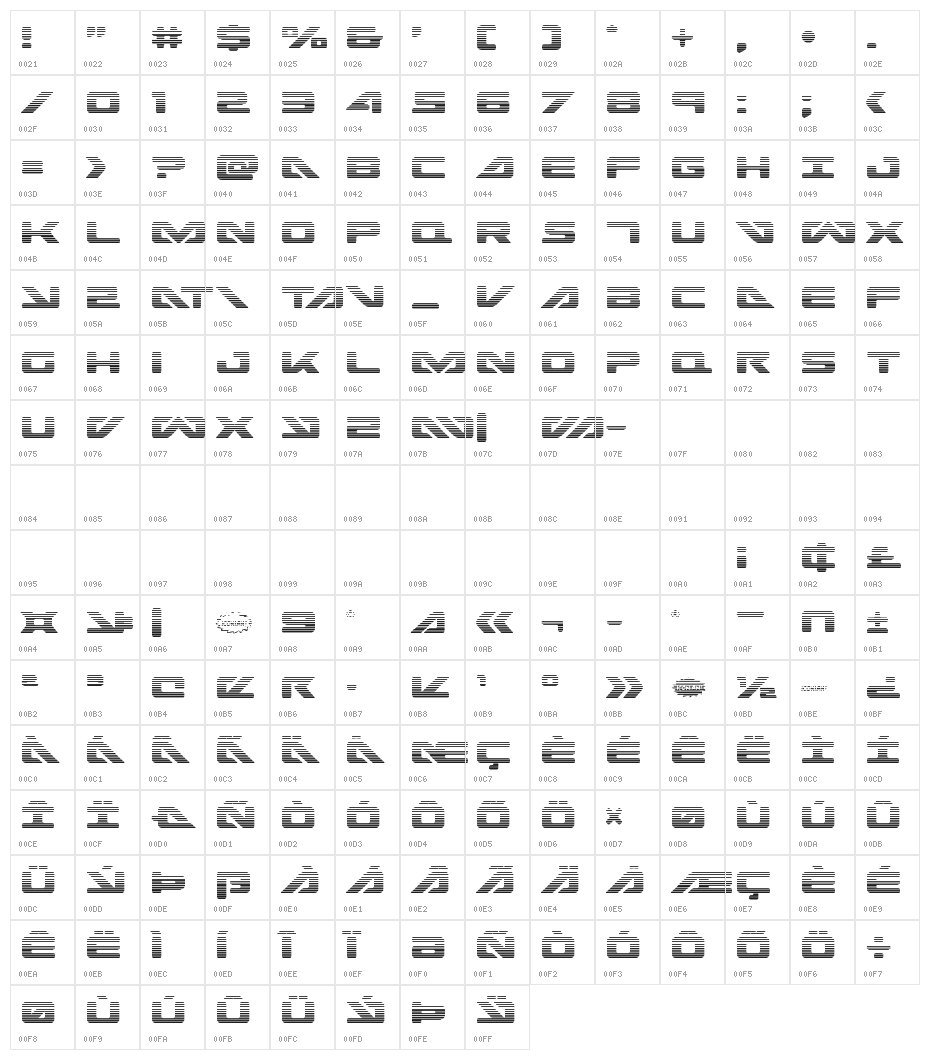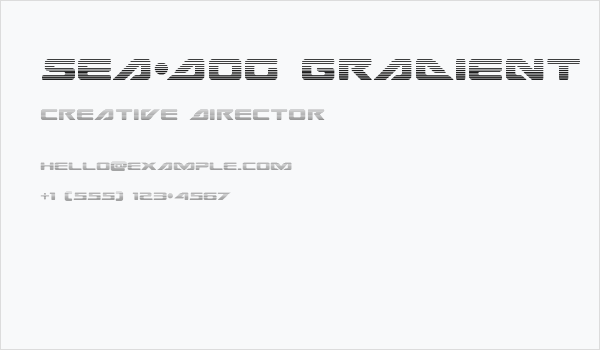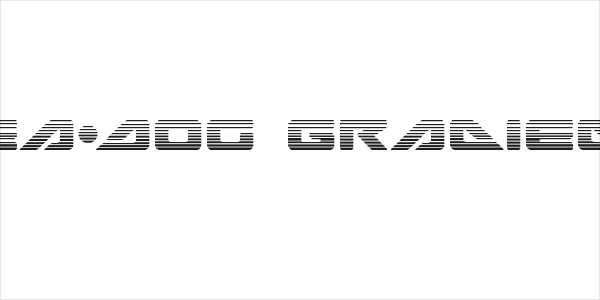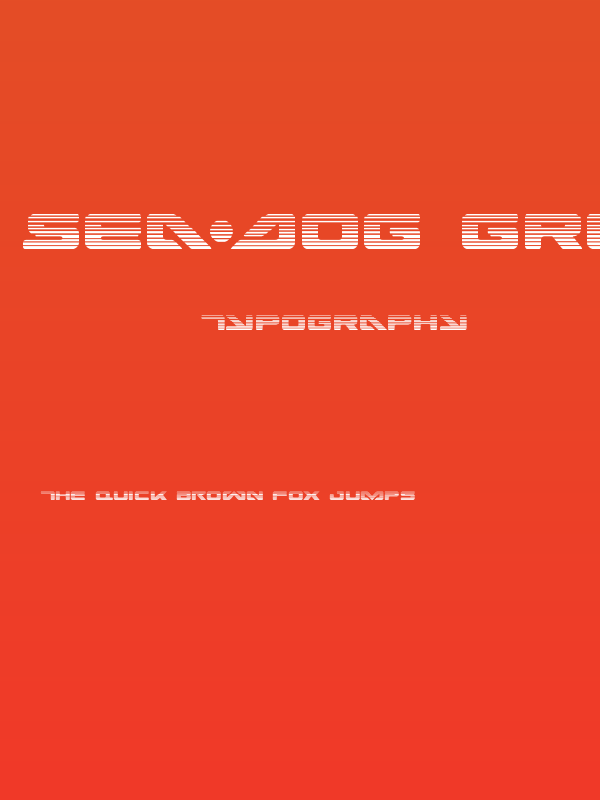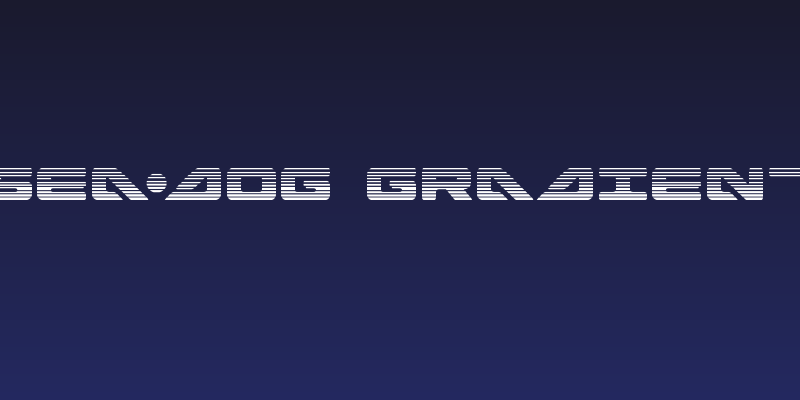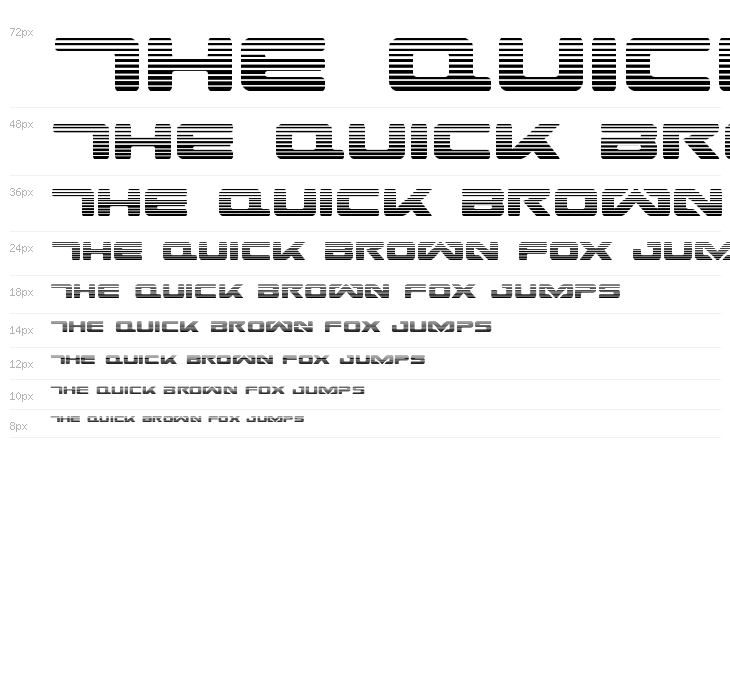
Sea-Dog Gradient Font
| Proyectos propuestos | Ideal for technology branding, sci-fi themed projects, video game titles, and modern advertising campaigns. |